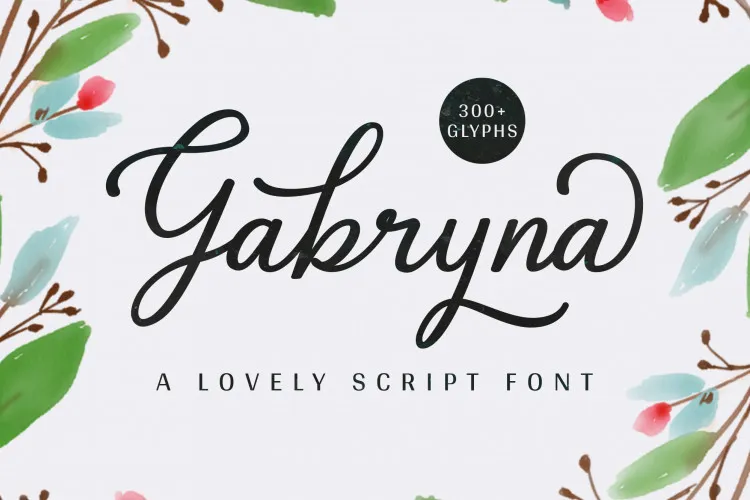
Gabryna Script Font – Fonte Grátis
Gabryna Script Font
Bem-vindo a mais uma descoberta fascinante no vasto universo das fontes digitais! Nesta categoria de Script Fonts, estamos apresentando a Gabriya Font. Inspirada nas preciosas escrituras que são as anotações de estilo e elegância na nossa cultura atual, a Gabriya é perfeita para diversos projetos. Proporcionada por Sibelumpagi Studio, a Gabriya Script Font é uma fonte tipográfica baseada em gravação chinesa, com alguns caracteres alternativos que adicionam um toque de beleza à sua composição. Esta fonte vem acompanhada dos 324 caracóis estandartes incluídos, suporte multilingue para diversidade de comunicação global e ligaturas, que podem ser usadas para aprimorar ainda mais seu design. A Gabriya é o resultado de um trabalho meticuloso e criativo, oferecendo aos profissionais da gráfica e designers um recurso adicional capaz de transformar qualquer projeto em uma obra-prima. Seja você um escritor, designer de jogos ou mesmo um artista, a Gabriya Script Font é o companheiro ideal para criar designs cheios de vida e beleza. Descubra agora e veja por si só como essa fonte pode revolucionar seus projetos!